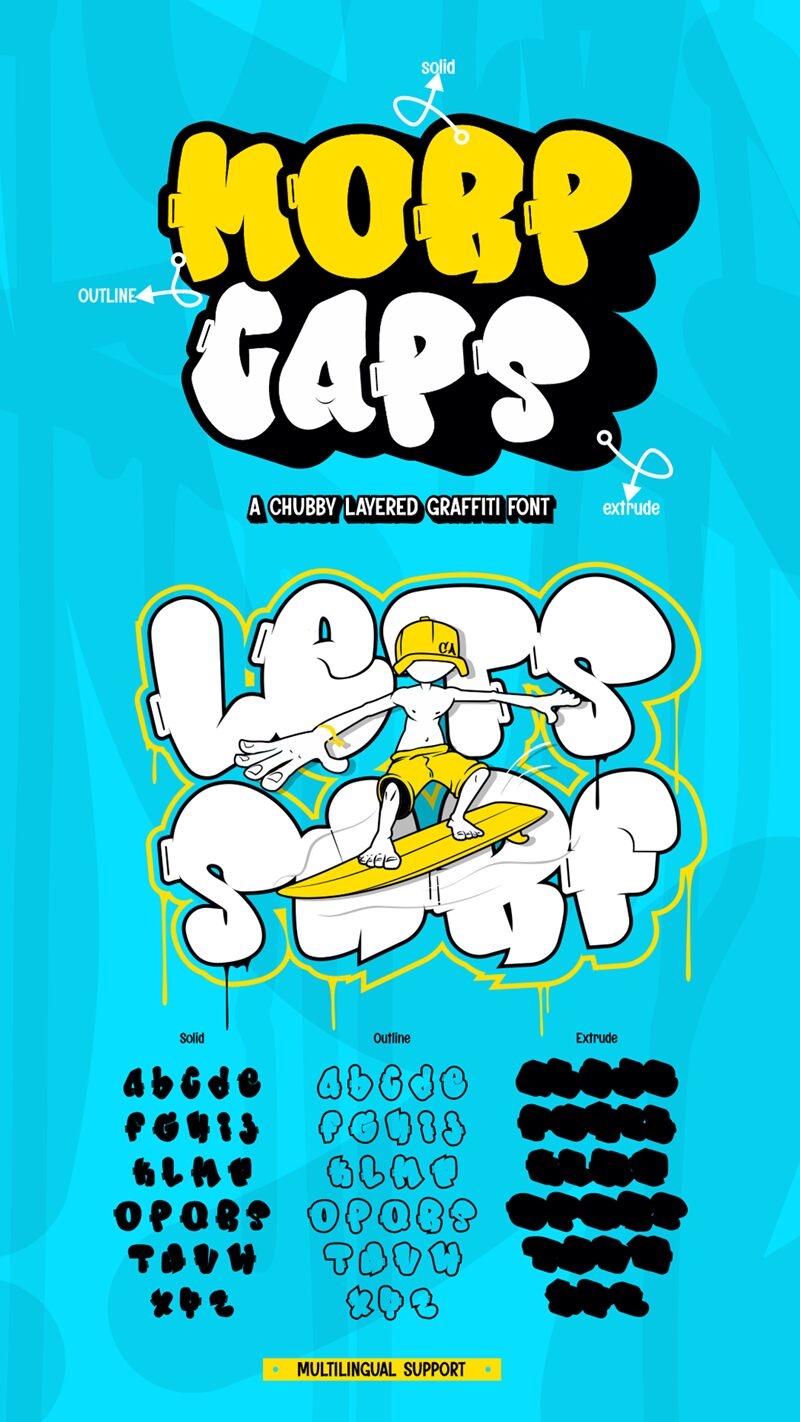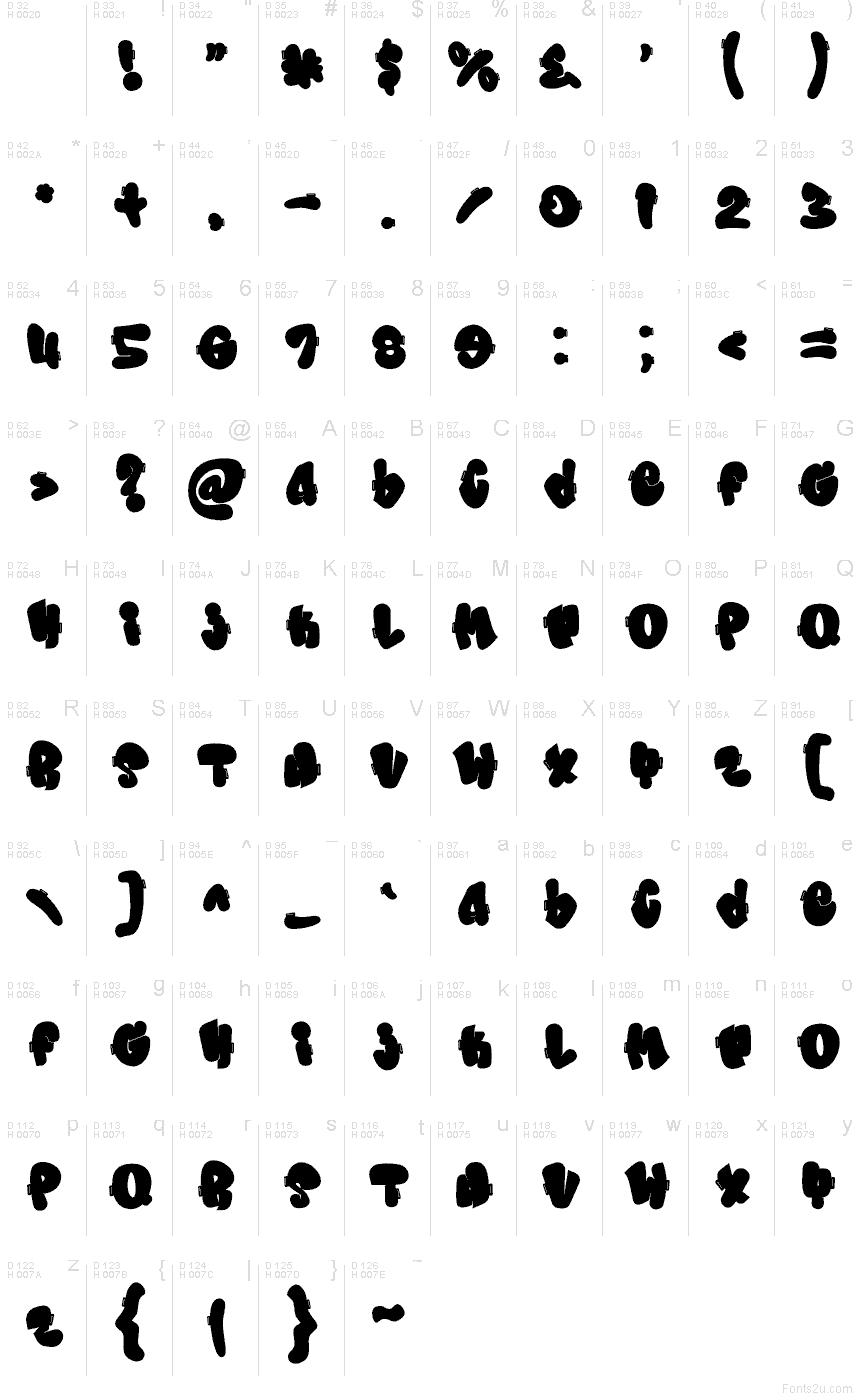
Il font Morp Caps, creato da Rizal Yusepudin Salman & Muhammad Panji Ramdhani di Sipanji x Figuree, è una tipografia graffiti gratuita che ricorda la vernice fresca impressa attraverso uno stencil. Le sue forme tozze e arrotondate, insieme alle interruzioni nel tratto, conferiscono a ogni parola un'attitudine street-art decisa, mentre il ritmo irregolare la mantiene giocosa anziché aggressiva.
Usa Morp Caps per dare una forte personalità a poster di skate, copertine di album, capi streetwear, anteprime di giochi, titoli YouTube, volantini per eventi giovanili o per aggiungere un tocco audace al packaging. Questo font gratuito è perfetto per frasi brevi e d'impatto; abbinalo a un sans serif pulito e neutro per qualsiasi informazione di supporto.